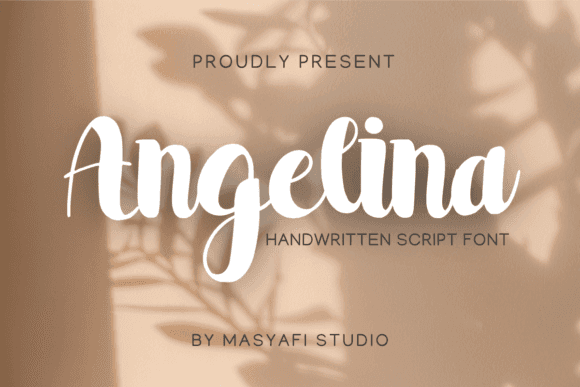
Fuente Angelina para Cricut, Silhouette y diseños imprimibles
Angelina es una fuente elegante y versátil para manualidades, diseñada para ser compatible con Cricut, Silhouette y plataformas de diseño digital. Su estilo fluido y suave es ideal para proyectos que requieren un aspecto refinado y femenino, como etiquetas, tarjetas y diseños de ropa.
Esta fuente combina encanto creativo con usabilidad práctica, ofreciendo cortes limpios y legibilidad tanto en formato digital como físico. Ya sea que esté creando decoración para el hogar, señalización para bodas o imprimibles, Angelina realza cada proyecto con una sutil sofisticación.
Angelina se integra perfectamente en los principales entornos de software de diseño y máquinas de corte, lo que la convierte en una fuente preferida por los diseñadores de manualidades y bricolaje.
Por qué te encantará
- Hermoso flujo para proyectos elegantes.
- Perfecto para aplicaciones de corte e impresión.
- Funciona con todas las principales plataformas de manualidades.
- Estructura de fuente elegante y fácil de leer
P: ¿Para qué se utiliza mejor la fuente Angelina?
R: Angelina es perfecta para crear proyectos elegantes como etiquetas, señalización de bodas y decoración imprimible con Cricut o Silhouette.
P: ¿Puedo usarlo para citas y carteles imprimibles?
R: Por supuesto. Angelina es una excelente opción para impresiones elegantes, arte mural y señalización.
| Característica | Angelina | Sofía Lane | Guión de rubor |
| Estilo de fuente | Escritura elegante con curvas suaves. | Serifa femenina con florituras | Fuente de exhibición manuscrita elegante |
| Mejores usos | Invitaciones, etiquetas, prendas de vestir | Marcas, logotipos, papelería | Citas, arte mural, planificadores |